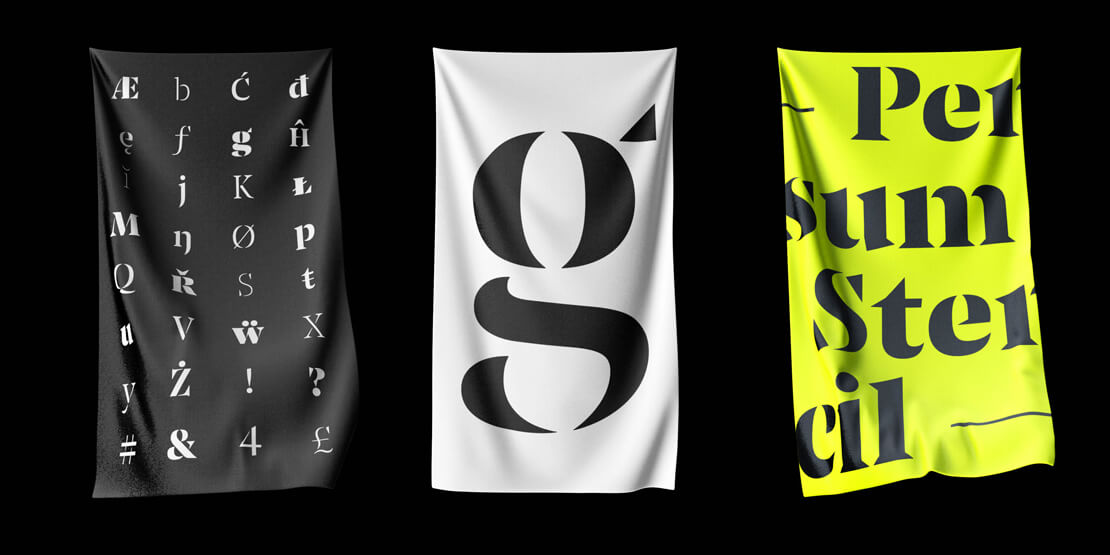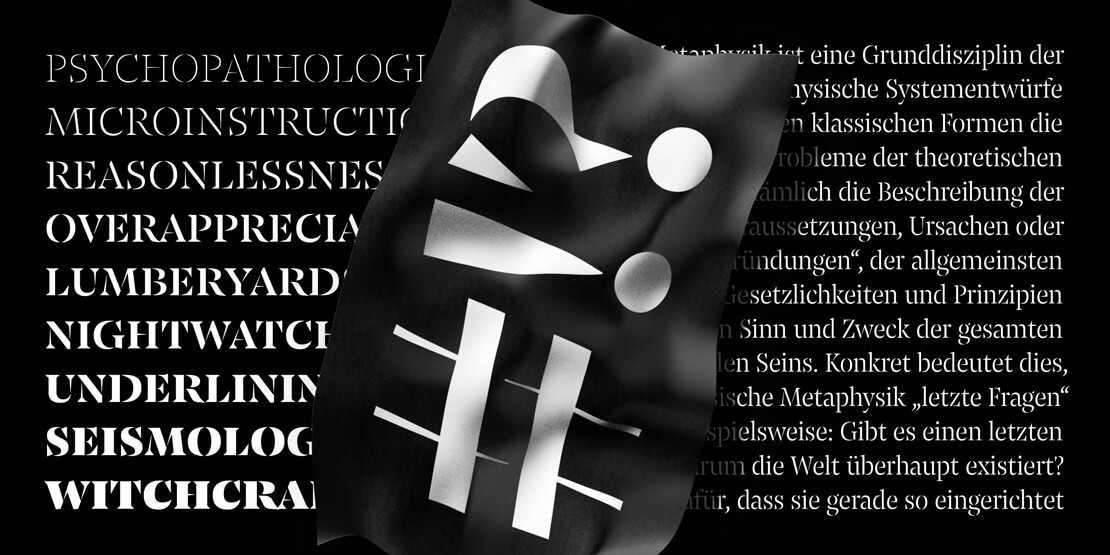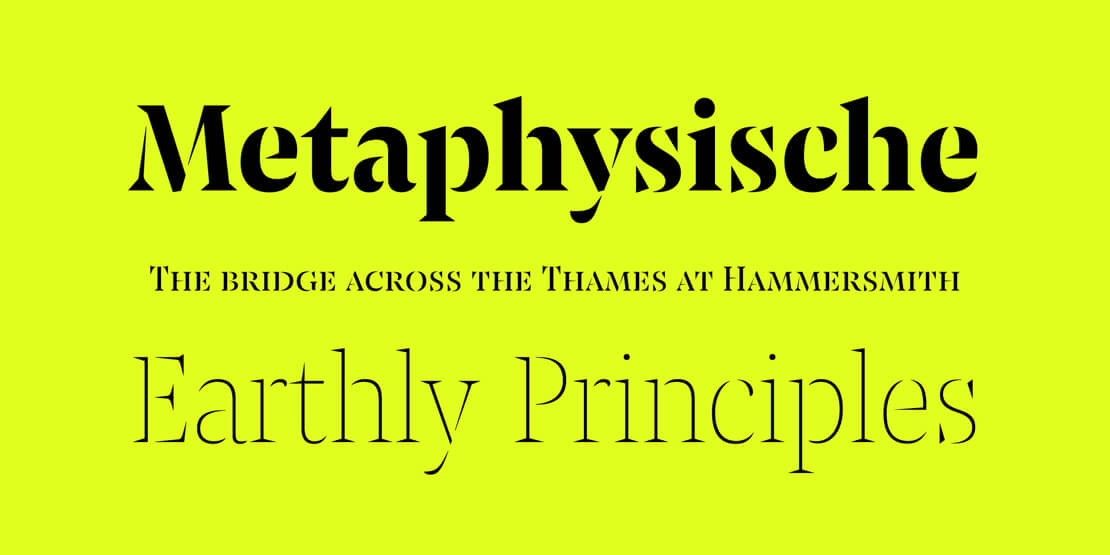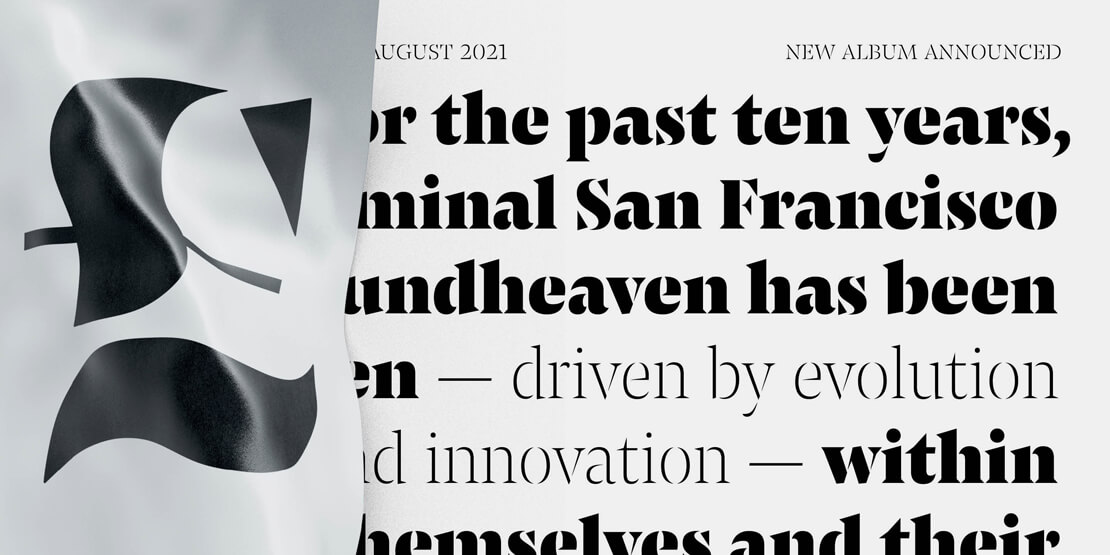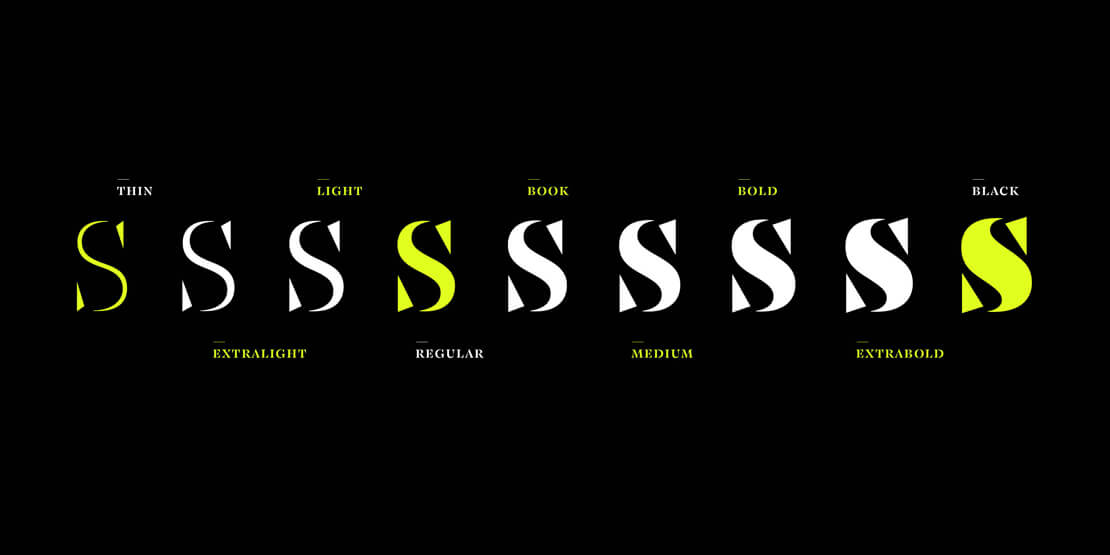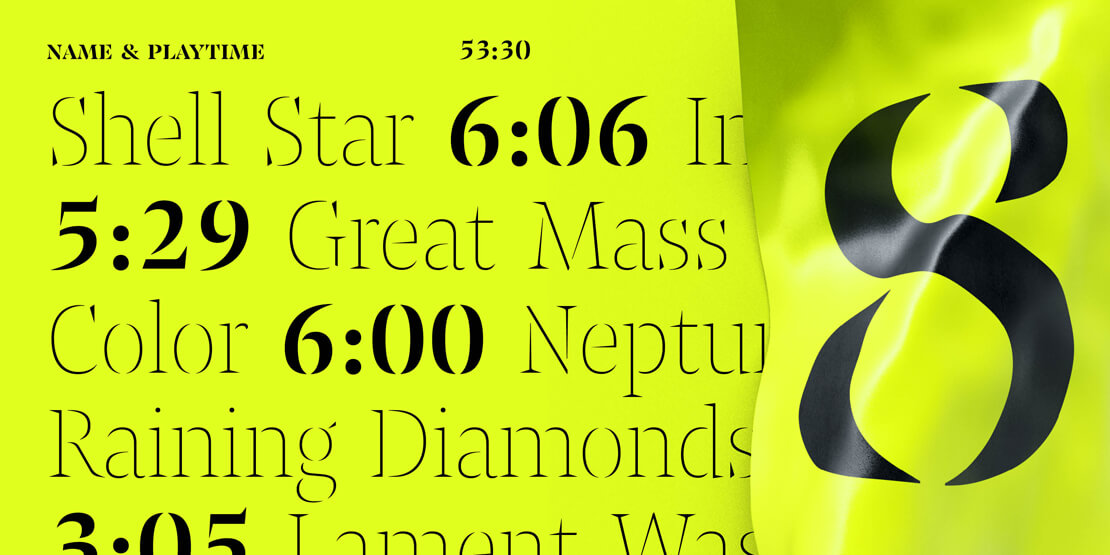
Pensum Stencil: Schablonenschrift von TypeMates
Die Typefoundry TypeMates präsentiert mit »Pensum Stencil« eine ausdrucksstarke und elegante Schablonenschrift zur »Pensum Display«.
Nils Thomsen hat die Schriftart für den plakativen Einsatz entwickelt. »Pensum Stencil« wurde von der Pensum Display abgeleitet. Der Kontrast ist überblendet, so dass die Buchstaben in einzelne sichelförmige Formen zerbrechen und eine Kombination aus pinselartigen Elementen sowie spitzen Details entsteht.
Somit eignet sich die »Pensum Stencil« beispielsweise für Bereiche wie Editorial Design, Branding, Packaging und überall dort, wo die fragmenthaften Zeichen im Detail zur Geltung kommen können.
Die Schrift gibt es in neun Schnitten – von der zarten »Light« bis hin zu den dunklen Schnitten der »Black«. Mehr als 800 Glyphen und diverse OpenType-Features sind enthalten. »Pensum Stencil« deckt zudem den Adobe Latin 3 Standard ab und bietet eine breite Unterstützung der lateinischen Sprachen an.